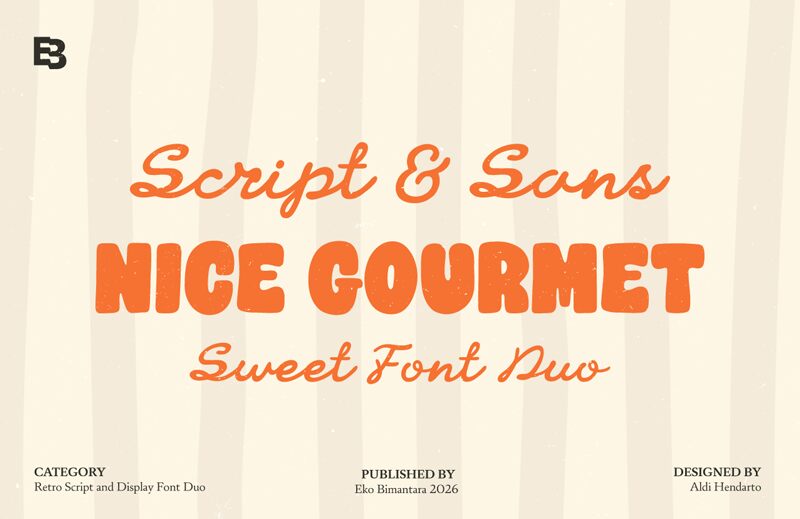
Nice Gourmet Script von Eko Bimantara ist eine kostenlose Handschrift-Font mit einem flüssigen, appetitlichen Rhythmus, der an den Charme handgemalter Ladenschilder erinnert. Die Buchstaben gehen in einer fließenden Bewegung ineinander über und kombinieren abgerundete Formen mit einigen markanten, längeren Strichen, was der Schrift eine entspannte und zugleich elegante Ausstrahlung verleiht.
Sie passt perfekt zum Branding von Cafés, auf Verpackungen für Backwaren, Menükarten, Kochbuch-Cover oder Flaschenetiketten – überall dort, wo der schwungvolle Charakter kurze Texte allein tragen kann. Als kostenloser Font eignet sie sich zudem hervorragend für Titelkarten, Logo-Entwürfe und Monogramme, besonders wenn Sie einen freundlichen und einladenden Look suchen, der weniger formell als vielmehr herzlich wirkt.